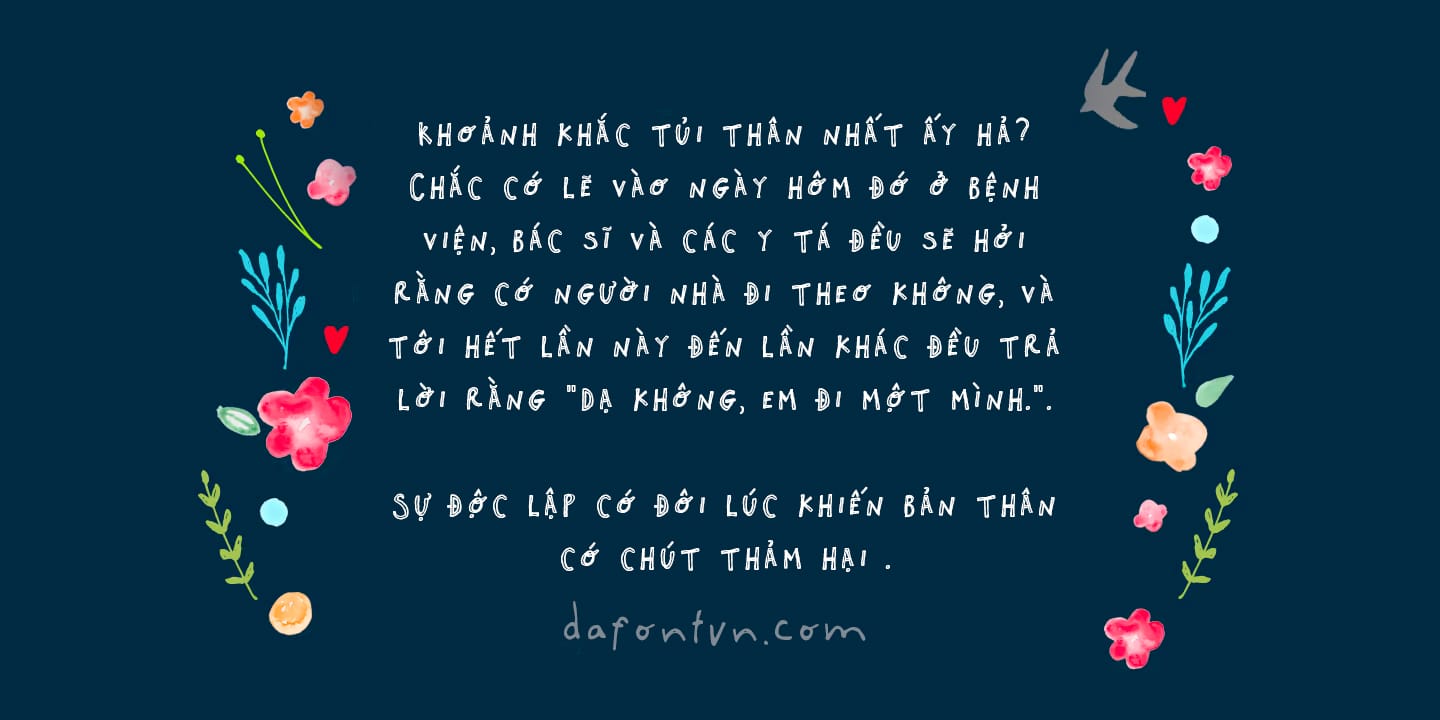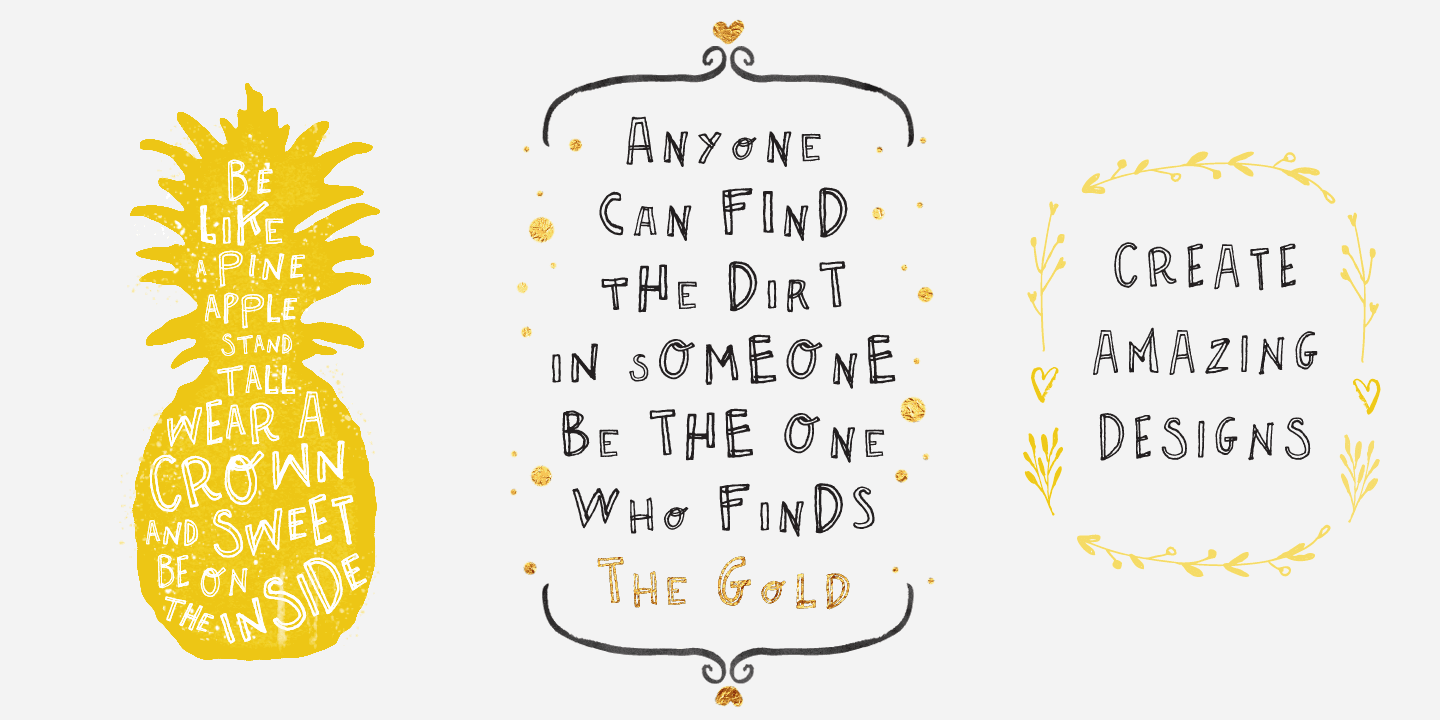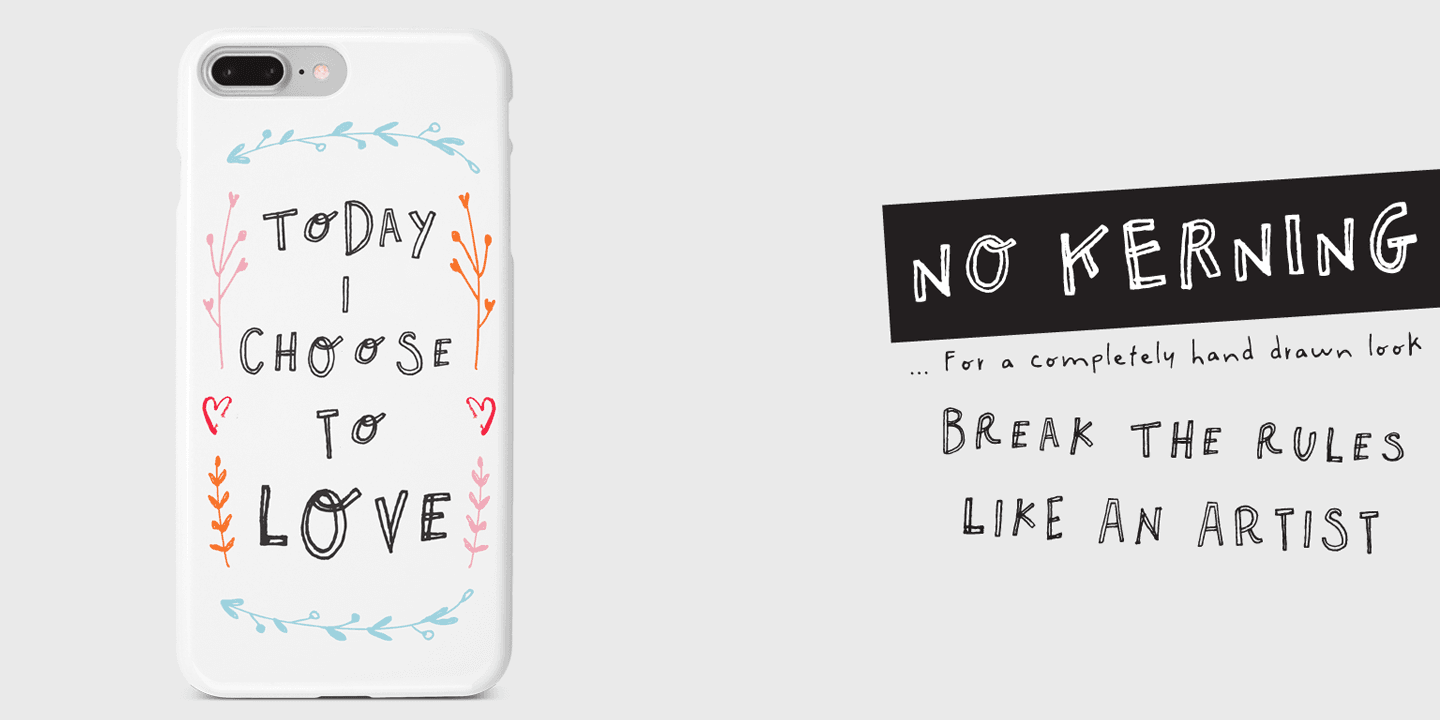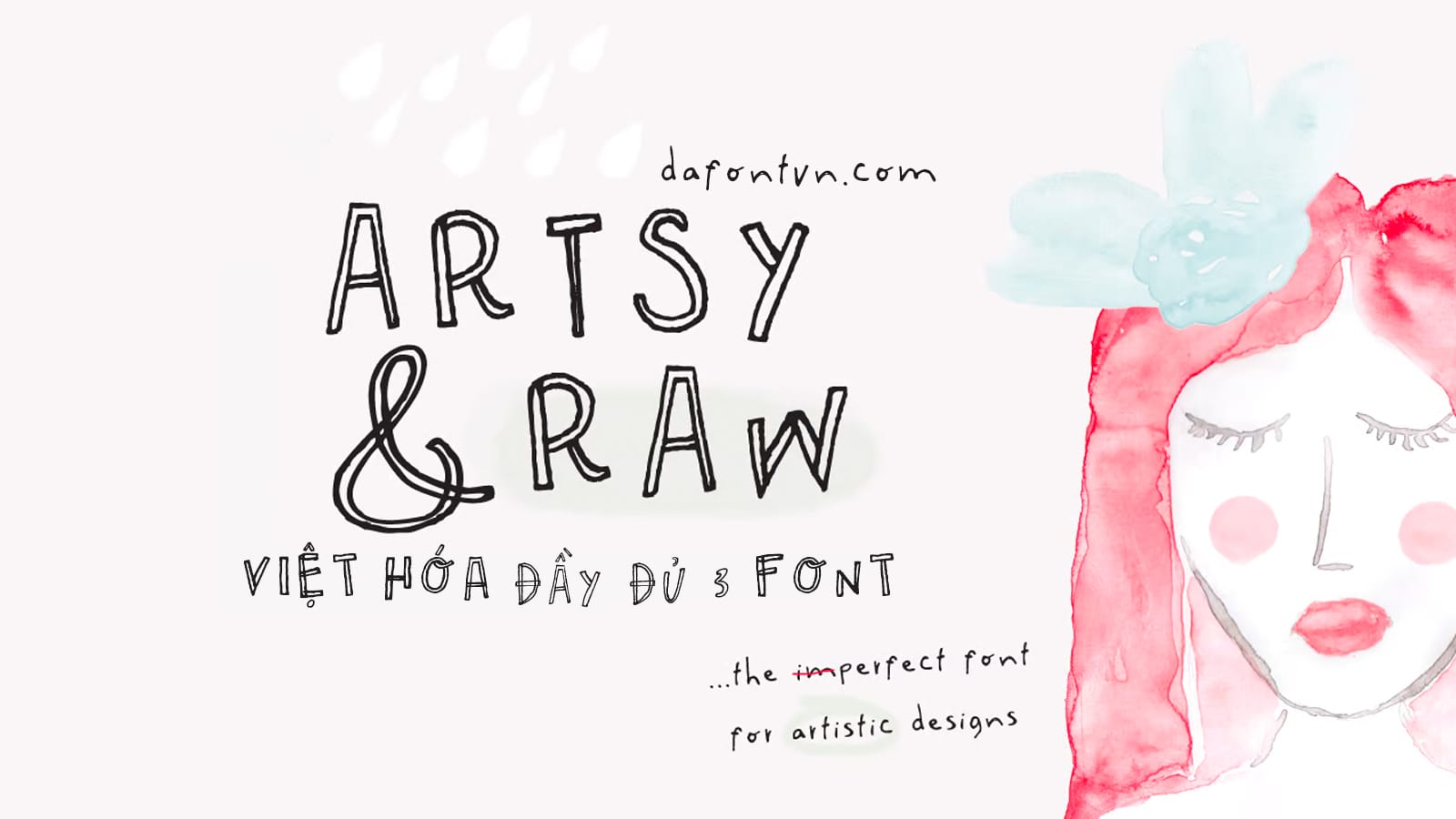
Font Font Artsy and Raw Việt hóa – một font chữ viết tay dễ thương và rất đẹp phù hợp với hầu hết các thiết kế như quote, bìa sách, thiệp mời, bao bì, tờ rơi… Font được việt hóa bởi iCiel với đầy đủ 3 kiểu, mình đã kerning, chỉnh sửa lại đôi chút.